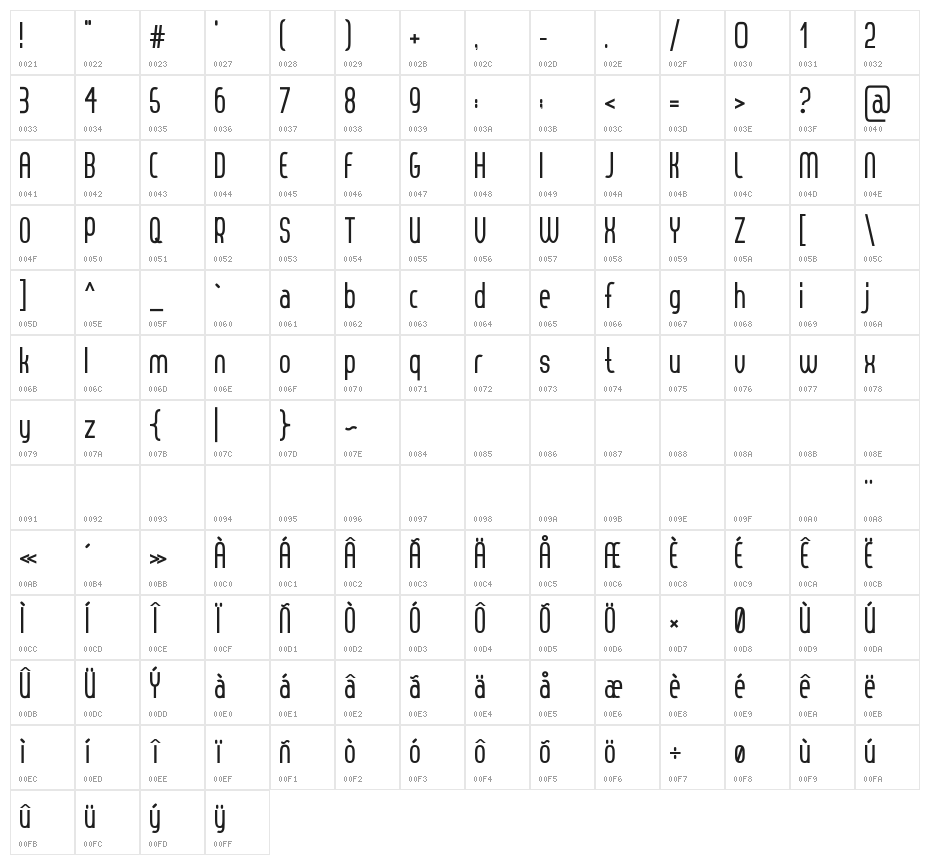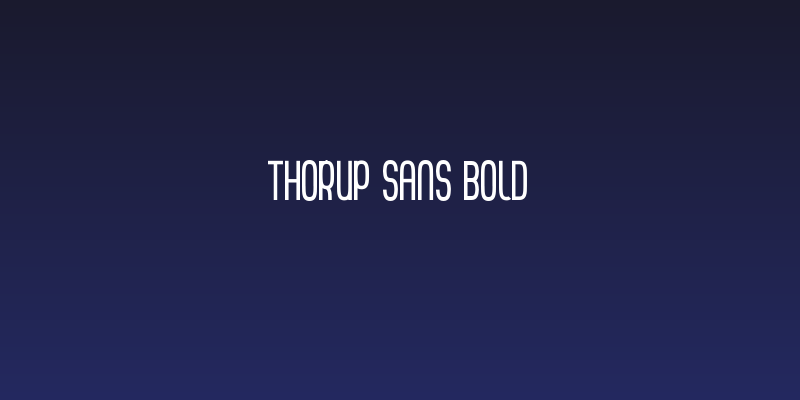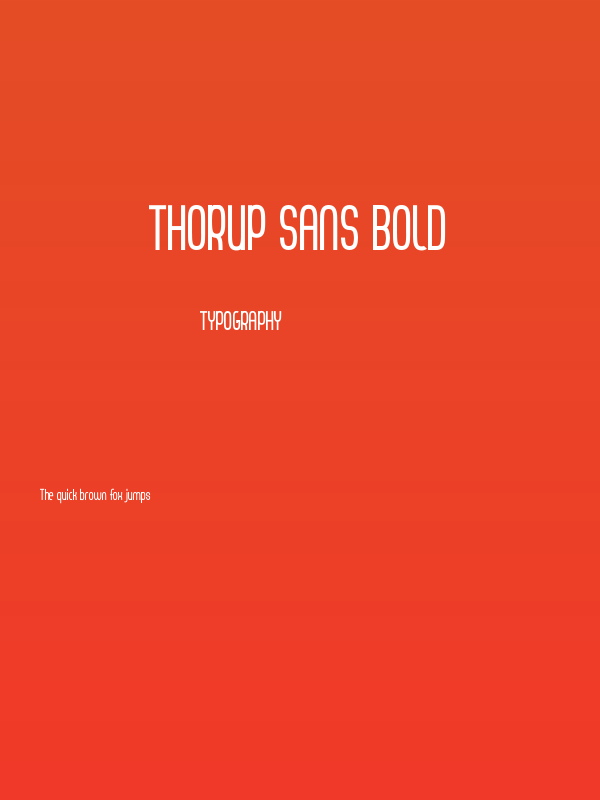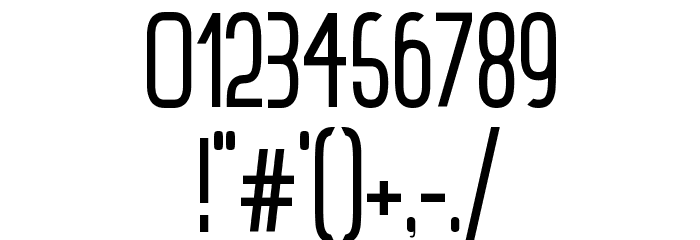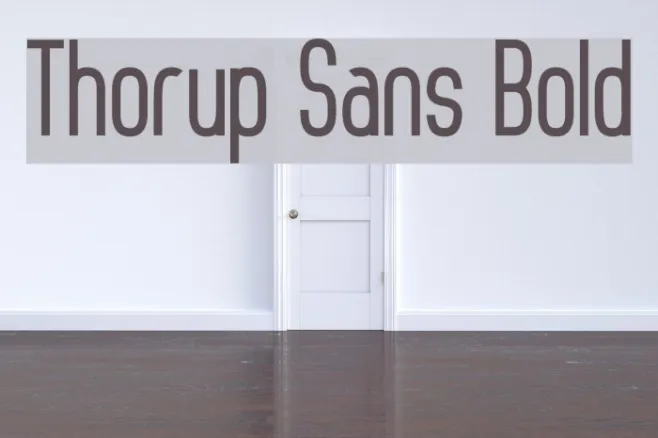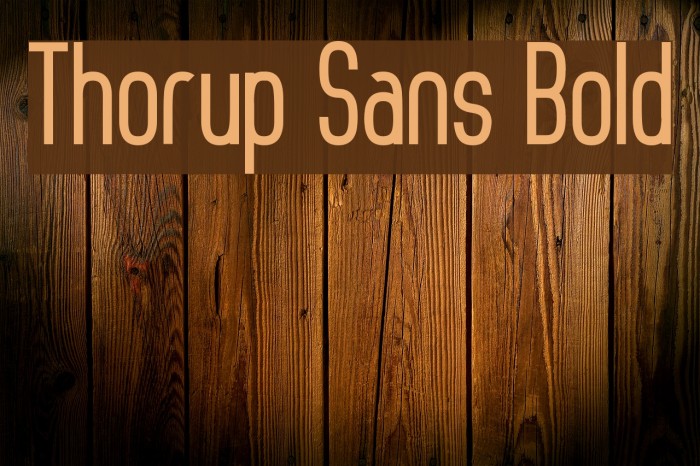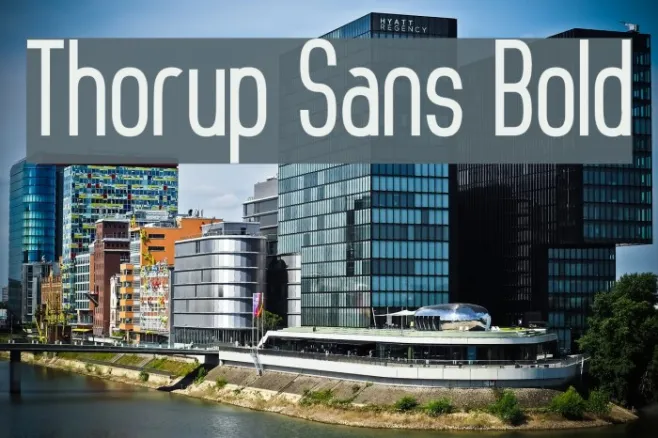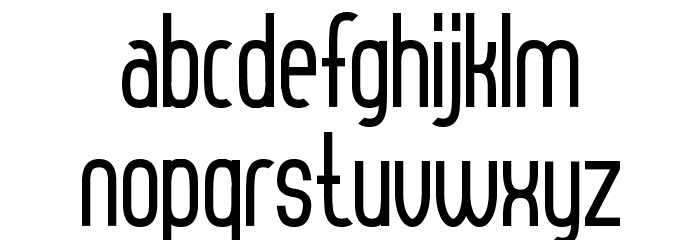
Thorup Sans Bold Font
✎ Sans Serif
| Anwendungsfall | Headlines, Logos, Branding |
| Vorgeschlagene Projekte | Ideal for branding, advertising, digital media, and print materials where a modern and approachable look is desired. |